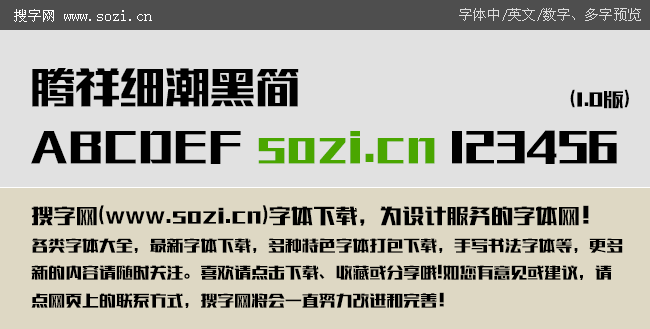
騰祥細(xì)潮黑簡(jiǎn)
搜字網(wǎng)提供一款騰祥細(xì)潮黑簡(jiǎn)中文藝術(shù)字體下載,騰祥細(xì)潮黑簡(jiǎn)是在潮黑基礎(chǔ)上減細(xì)設(shè)計(jì)而成,字形結(jié)構(gòu)扁方、端莊,橫豎筆畫(huà)粗細(xì)比例適度、豎筆粗壯有力,布白均勻、行文貫通,并且部分點(diǎn)和提、撇和點(diǎn)做連筆畫(huà)處理,更好的展現(xiàn)出字形的連貫性和整體感。騰祥細(xì)潮黑簡(jiǎn)筆畫(huà)簡(jiǎn)潔有力細(xì)微處變換靈動(dòng),即實(shí)用又富有裝飾效果,能夠適合標(biāo)題和屏顯用字,可用于印刷出版、包裝設(shè)計(jì)、廣告設(shè)計(jì)、網(wǎng)頁(yè)設(shè)計(jì)、屏幕顯示等。